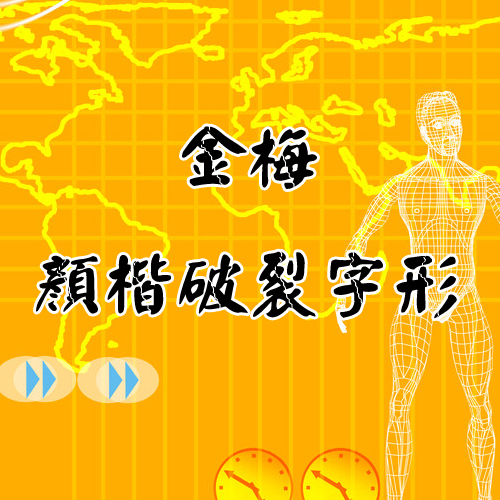
軟件介紹 軟件標簽: 金梅 金梅顏楷破裂字形在金梅顏楷字體基礎上加入裂痕元素的字體。該字體多用于創(chuàng)造、設計行業(yè),有時候殘缺也是一種美,看起來還是很不錯的。趕快下載體驗吧!字體安裝方法方法一:控制面板/字體/文件/安裝新字體;方法二:直接將字體復制到C:\WINDOWS\Fonts。 軟件截圖 上一張下一張(1 / 1) 安裝詳細截圖 猜你喜歡 金梅字體 裂痕字體 金梅字體 金梅字體是以繁體字形為主,多數(shù)的金梅字體都是繁體。金梅字體給人的感覺比較多樣,有的比較圓潤,有的比較可愛,還有破裂的字體,于楷體形成了鮮明的對比,沒有固定的樣式。金梅字體多用于廣告制作、海報制作、封面制作等。 查看更多>> winman tun10011字體 17.57M/中文/6.6/下載 金梅浪漫原體國際碼 1.91M/中文/6.6/下載 金梅粗明原體國際碼 1.41M/中文/5.0/下載 金梅流行書 2.78M/中文/10.0/下載 金梅綜藝菱心 4.19M/中文/10.0/下載 金梅浪漫小胖 3.44M/中文/10.0/下載 裂痕字體 裂痕字體又叫破裂字體,簡單的來說就是將文字加上裂痕,做成破裂或撕裂效果。霹靂字體其實也屬于裂痕字體,只是給文字加上閃電劃破的效果,實際效果跟裂痕字體差不多。裂痕字體會給人一種撕心裂肺,或者說是破碎,傷心的感覺。 查看更多>> 金梅特黑裂開體字體 2.25M/中文/3.4/下載 金梅顏楷破裂字形 3.87M/中文/10.0/TTF格式下載 金梅超黑破裂字體 2.40M/中文/5.0/下載 金梅超明破裂字形 3.61M/中文/3.3/TTF版下載 金梅顏楷破裂字形(繁) 3.87M/繁體/10.0/下載 金梅毛行破裂字形(繁) 3.71M/中文/10.0/TTF版下載 其他版本下載 標題 大小 更新日期 下載 下載地址 電腦版 金梅顏楷破裂字形 TTF格式 點擊報錯 軟件無法下載或下載后無法使用,請點擊報錯,謝謝! 關閉報錯反饋 請描述您所遇到的錯誤,我們將盡快予以修正,謝謝! *必填項,請輸入內容 本類最新 金梅海報美工體 金梅新箭頭字范例字體 免費版 金梅特黑水花字形字體 免費版 金梅粗尖頭字范例繁體字體 免費版 金梅淡古字ttf 免費版 金梅浪漫鏡射體 用戶評論 熱門評論 最新評論 發(fā)表評論 查看所有評論(0) 昵稱: 請不要評論無意義或臟話,我們所有評論會有人工審核. 字數(shù): 0/500 (您的評論需要經過審核才能顯示)